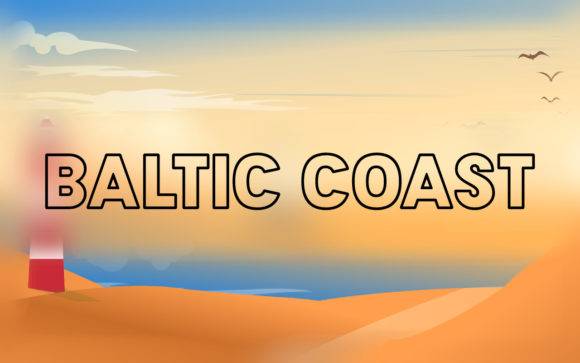
Baltic Coast é uma fonte de exibição criativa e moderna, perfeita para adicionar um toque único aos seus designs. Com seus caracteres bem equilibrados, ela se adapta a uma ampla gama de projetos, de logotipos a pôsteres. Baixe gratuitamente e deixe suas ideias ganharem vida com a fonte Baltic Coast.
Fonte Baltic Coast para títulos, pôsteres e projetos de identidade visual.
Fonte da Costa Báltica